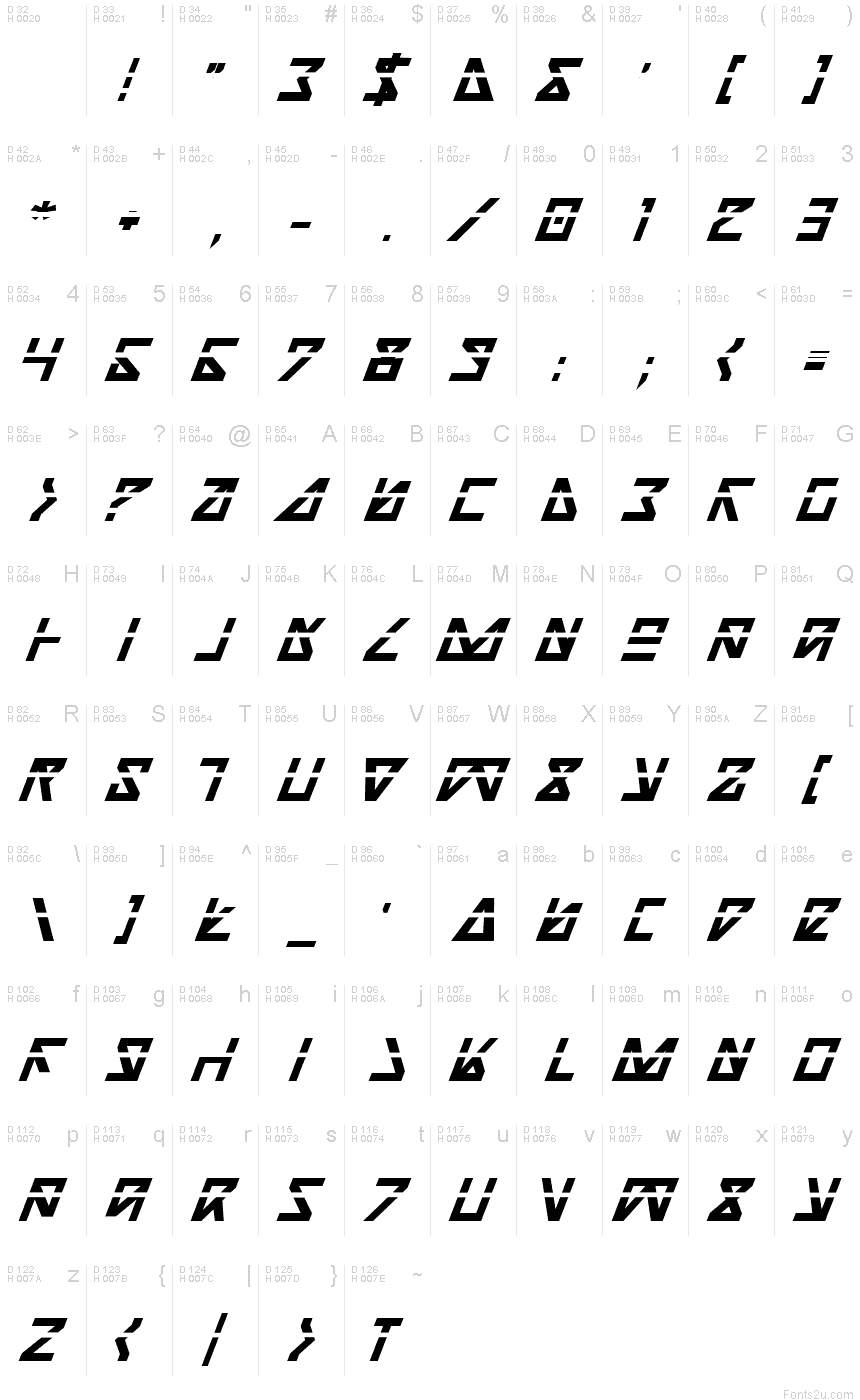
Nick Turbo Bold Italic Las od Iconian Fonts to darmowy techniczny krój pisma typu display, który wygląda, jakby był w ciągłym ruchu. Ostre, kątowe pociągnięcia, silne pochylenie do przodu i „pocięte” kształty liter tworzą efekt dużej prędkości, przypominający chromowane napisy w smudze światła. Ciasny, agresywny odstęp między znakami sprawia, że słowa zlewają się w jedną, aerodynamiczną całość – doskonałe rozwiązanie, gdy zależy Ci na tym, by tytuł przyciągał wzrok od pierwszego spojrzenia.
Nick Turbo Bold Italic Las doda energii logotypom gamingowym, identyfikacji wizualnej drużyn e-sportowych, plakatom science-fiction, grafikom wyścigowym, miniaturkom na YouTube o tematyce technologicznej oraz futurystycznym opakowaniom. Ten darmowy font najlepiej sprawdza się w dużych rozmiarach, jako wyrazisty nagłówek lub znak graficzny. Zestaw go z prostym, czystym krojem bezszeryfowym w tekście pomocniczym, aby całość pozostała czytelna i profesjonalna.
Nick Turbo Bold Italic Las